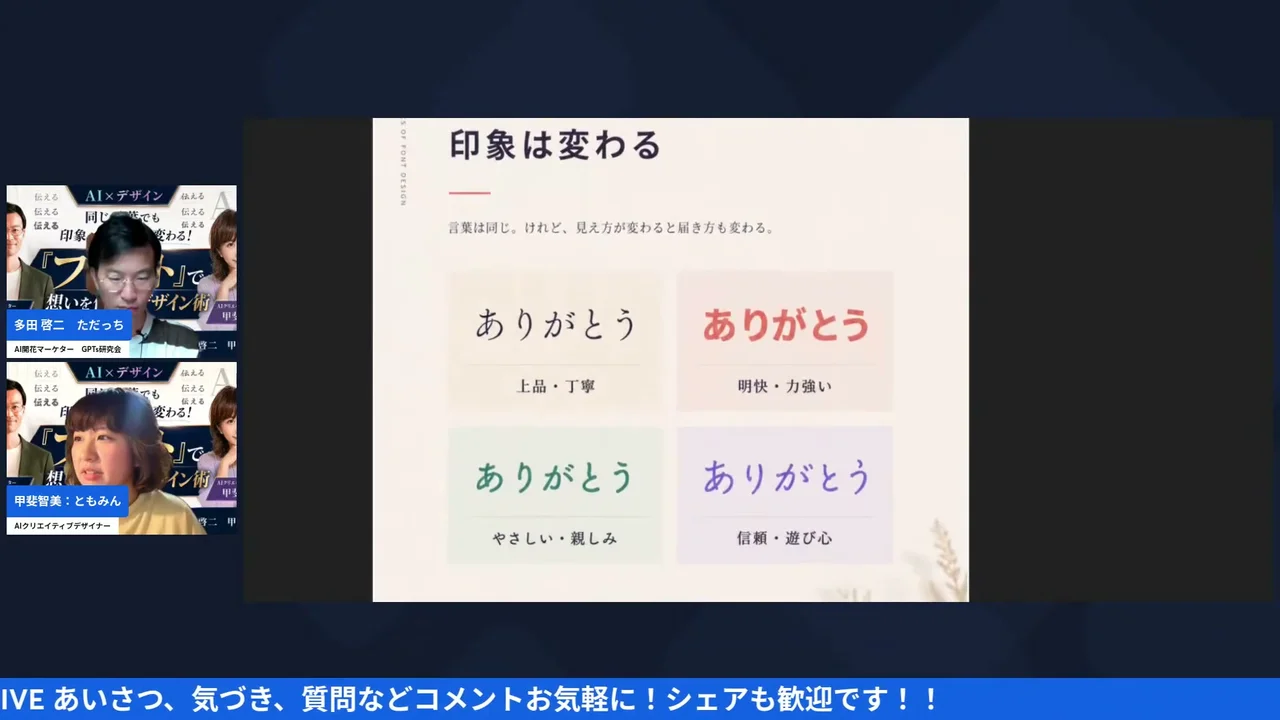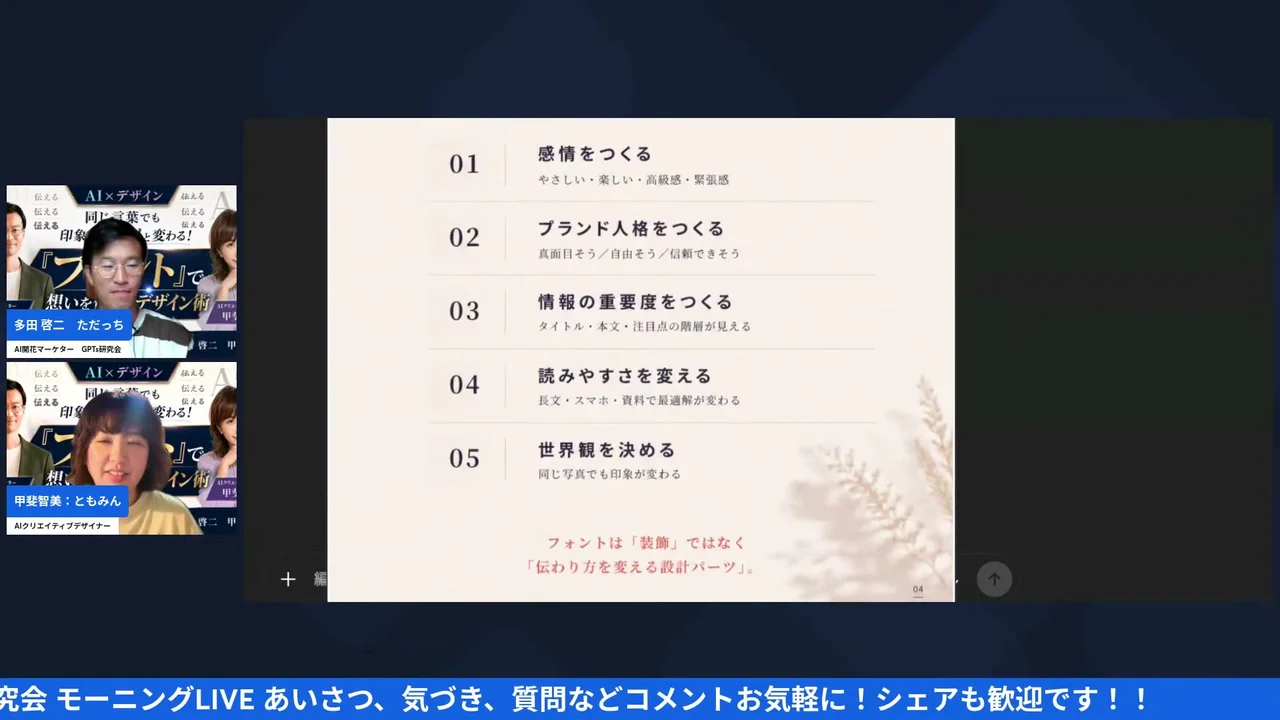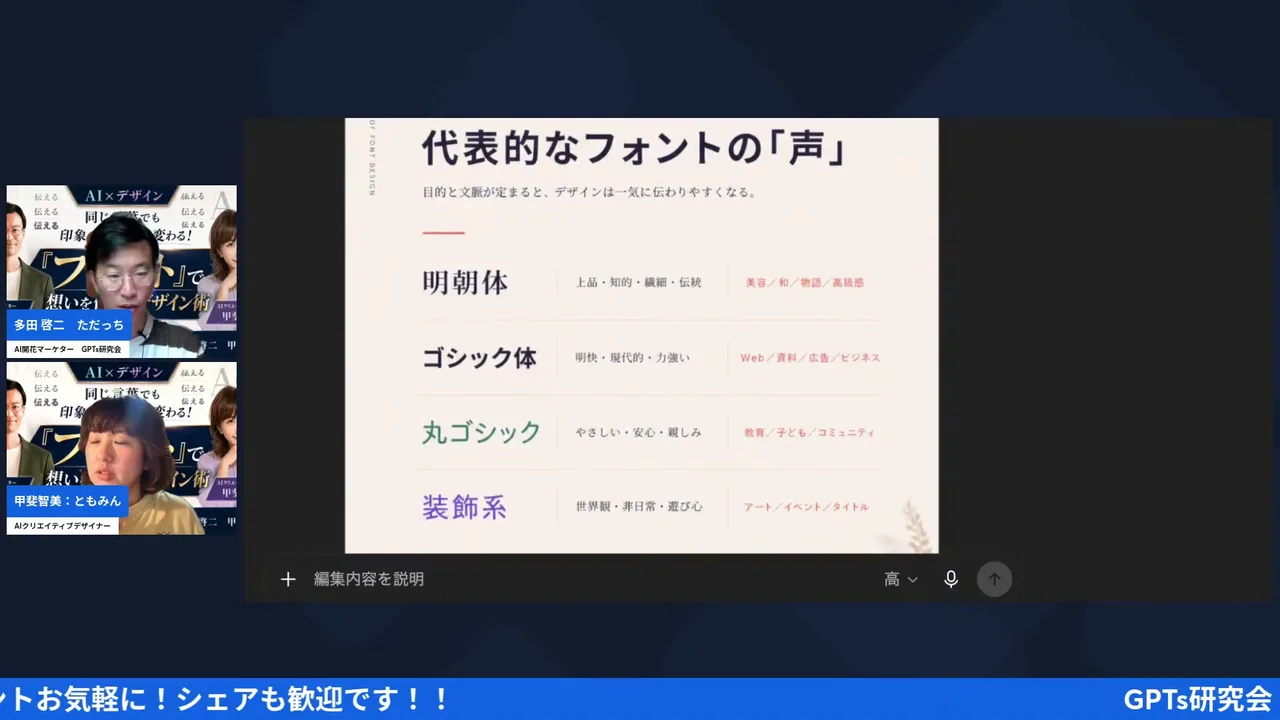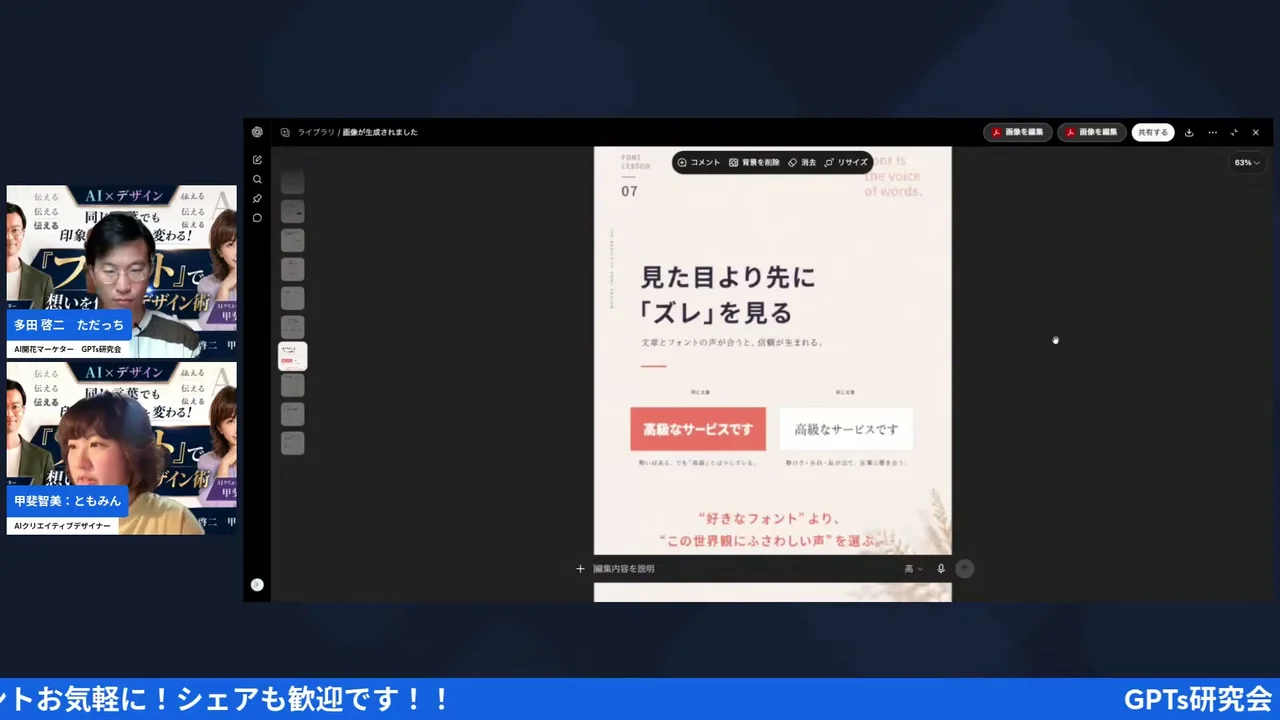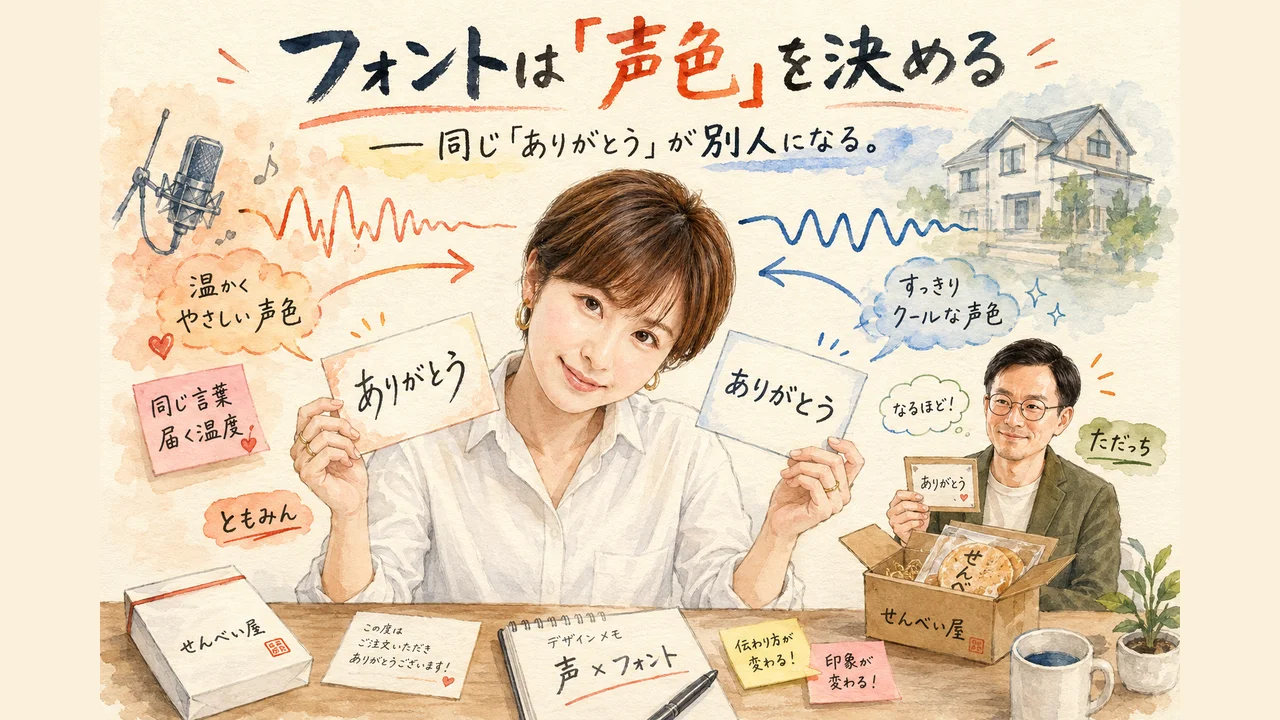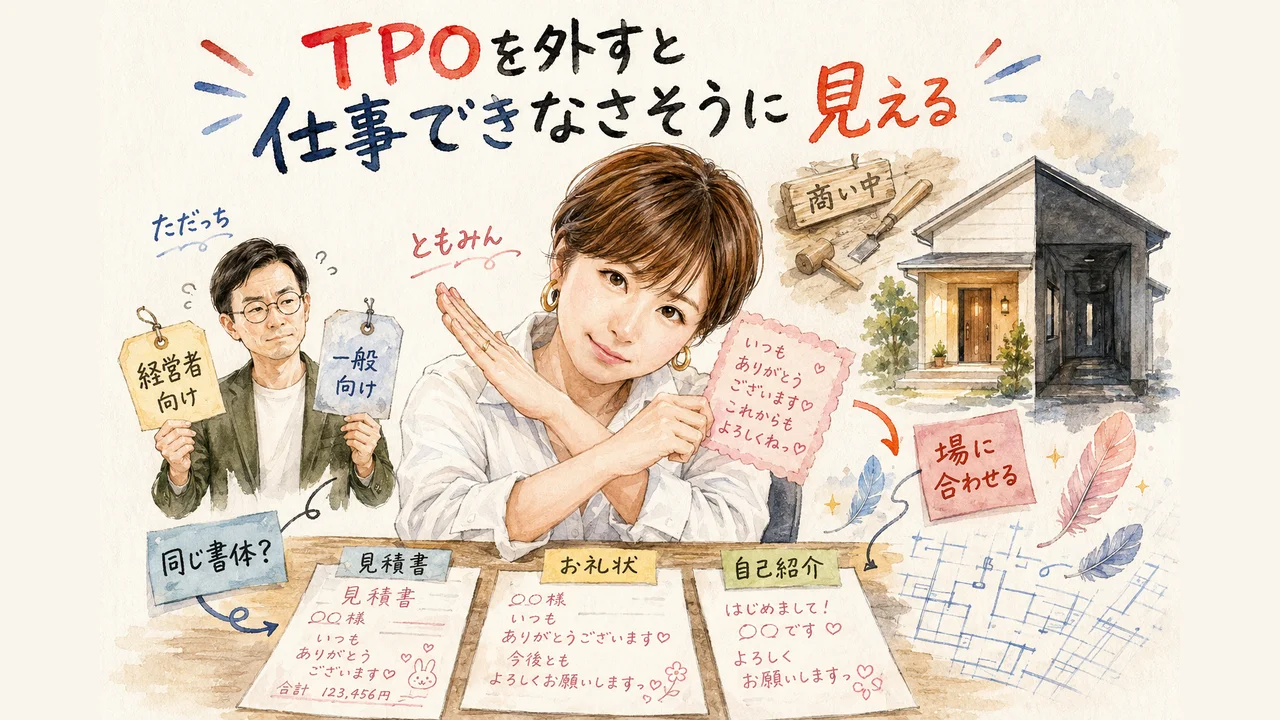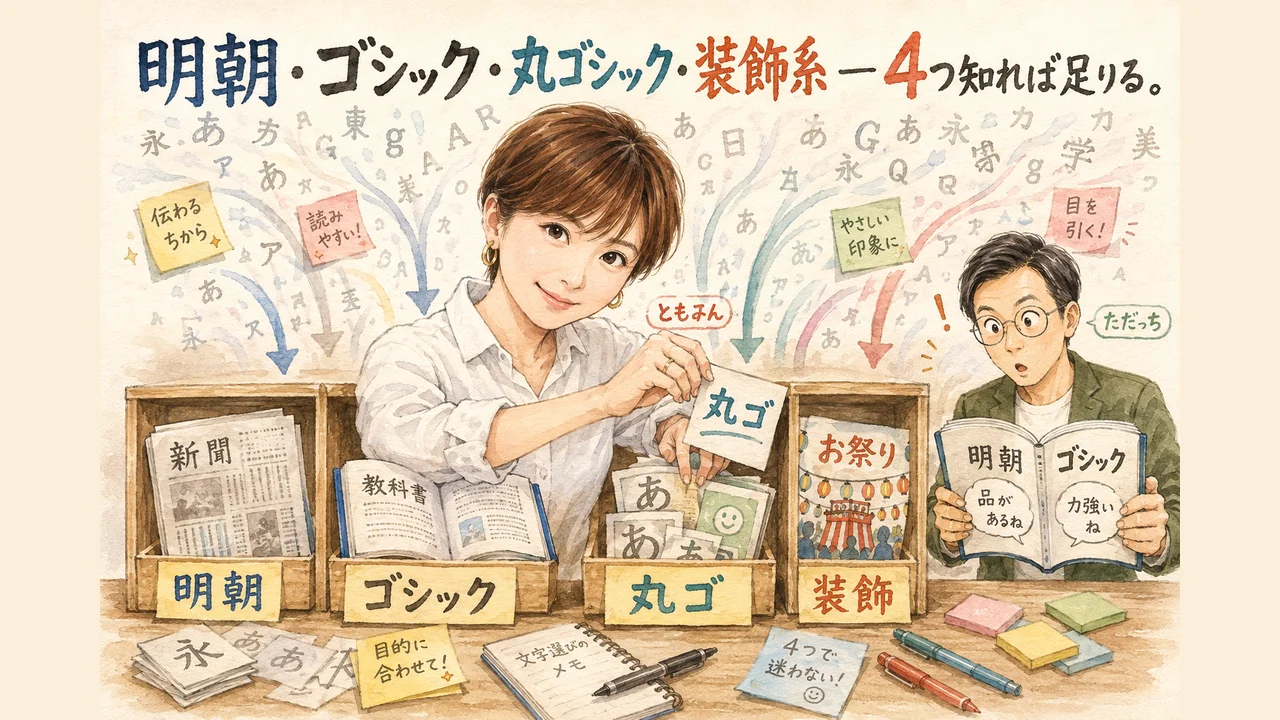
フォントの選び方で印象が激変する
明朝・ゴシック・丸ゴシックの使い分けとCanva実演|GPTs研究会 金曜あさLIVE
家事と子育てのスキマで経営する3方よしAI共創コンサルタントの田中啓之、ひろくんです。今回はただっち(多田啓二さん)とともみん(甲斐智美さん)の金曜あさLIVEを見て、私が受け取ったものを紹介するね。テーマは「AI×デザイン」。もっと絞ると、フォントの話です。
いやー、これがね。自分ずっと見落としてたなと思わされた。文字なんて、読めればそれでいいと思ってたんですよ。でね、ともみんが最初に置いた一言がこれ——フォントは声色を決める。文字は、読まれる前に、聞かれている。そういう話でした。同じ言葉でも、伝わり方はフォントひとつで変わる。
3行でわかるポイント
1. フォント=声色:文字情報は「何を言っているか」、フォントは「どう感じてほしいか」。同じ「ありがとう」でも別人になる
2. 使い分けは4種類でいい:明朝・ゴシック・丸ゴシック・装飾系。ベースは明朝とゴシック、あとはプラスアルファ
3. AIに指示する前段階:「なんか変」に自分で気づけるかどうか。文字と写真の一致感がないと、無意識で違和感が残る
フォント選びの全体像グラレコ|声色・TPO・4分類・3つの質問・Canva実演
フォントは「声色」を決める — 同じ「ありがとう」が別人になる
フォントは声色を決める|ともみん解説 同じ「ありがとう」をフォント違いで並べた比較画面
金曜の朝7時。画面の向こうで、ともみんがいきなり言い切ったんです。フォントは声色を決める、と。……いや、待って。文字に声も何もなくない? 私は正直そう思いました。ただっちも同じだったみたいで、すかさず「どういう意味でしょう?」って聞き返してる。で、そこからの説明が、ぐうの音も出ないくらい腑に落ちたんですよ。
▶ ともみん(7:28〜)
ともみん
「フォントは声色を決める。文字情報だったら何を言っているかということになるんだけど、どう感じてほしいか。だからね、ボーカルで言うと、声を選ぶことになるから。フォントにも普段用のフォントがあるんだよね。声を選ぶのと同じくらい大切だよっていうところですね」
ここ、2階建てになってるんだよね。1階が「何を言っているか」で、これは文字そのものが運ぶ。2階が「どう感じてほしいか」で、こっちを運んでいるのがフォント。同じ歌詞でも、歌う人の声が変わればまるで別の曲に聞こえる——あの現象が、紙の上でも画面の上でも起きている。そういう話でした。
例に出てきたのが「ありがとう」の4文字。細めの明朝で置いたときと、丸っこい手書き風で置いたときとで、届く温度がまるで違う。ともみんは、おせんべい屋さんからお客さんに送るダイレクトメールをたとえに出してました。同じ「ありがとう」でも、どっちのほうが相手に届く確率が高いか。考えたこともなかった。
▶ ともみん(9:31〜)
ともみん
「同じありがとうでも印象が変わるよって。同じだけど、見え方が変わると届き方が変わるから。ここだけでこれ、ちょっとフォントが全部違うものになってて、手書きのフォントだったり太さが違ったり色が変わったりっていうことになるんだけど、これだけで印象が変わるから。例えばお客さんにダイレクトメールとか、おせんべい買いましたって、お店の方から。このありがとうよりも、多分このありがとうが届く方が高いなみたいな感じ」
そこでともみんが持ち出したのが、Amazonで買い物したときに箱に入ってる小さなカード。ただっちも「カードみたいな」と即座に反応してました。あるある、って思わず声が出た。あの「ありがとう」って、けっこうな確率で手書きなんですよね。手書きだから、ほんの一瞬だけ目が止まる。ゴシックの活字だったら、ここまで気にならなかった気がします。
▶ ただっち(10:27〜)
ただっち
「そうだねー、確かに。手書きで考えると、本当に文字って個性が出たり人柄が出たりするから、そういう意味だと、このAI時代でも、このフォントっていうのって人から本当に伝わるよね。伝えてる思いがね」
ともみんはさらに、「ありがとう」にもTPOがあるって言ってました。カジュアルな「ありがとう」と、かしこまった「ありがとうございます」。言葉としては近いのに、フォントを変えるだけで、そのどっちに聞こえるかが変わってしまう。声を選ぶのと同じくらい大切だよ、と。
ただっちも「この視点はなかったですね」って素直に言ってました。私も同じです。デザインの話って、つい色とレイアウトに全部持っていかれるんだよね。文字は最後にちょこっと選ぶ、くらいの扱いだった。……そりゃ届かないわけだ、と思いました。
ここで私、けっこう反省したんです。チラシもLPも、色と写真と見出しの言葉で勝負するもんだと思ってた。文字そのものは「読めれば正解」の器だと。……でも受け取る側は、内容を理解する前に、もう声を聞いてしまっている。中身に届く前の一瞬で、この人はやさしそう、この会社はお堅そう、が決まってる。怖い。
💡 やさしく解説:文字情報とフォントの2階建て
同じ文章でも、読み手が受け取っているものは2つあります。ひとつは「何を言っているか」という中身。もうひとつが「どう感じてほしいか」という空気。前者を運ぶのが言葉で、後者を運ぶのがフォントなんだよね。だから、書いた文章がうまく届かないとき、原因は文章そのものじゃなく声色のほうにある場合がある、というのが今回のスタート地点でした。
TPOを外すと「この人、仕事できなさそう」に見える
フォントのTPO|伝達の設計というともみんの解説 TPO別フォント使い分けの解説画面
で、話は自然と「じゃあ誰に向けて書くのか」に移っていきました。ここでただっちが挟んだ整理が、経営者的にすごく実用的だったんです。読む相手が違えば、当然、選ぶ声も違う。
▶ ただっち(11:12〜)
ただっち
「そうだね。誰向けなのか、経営者向けなのか、一般の女性の方向けなのかによっても全然違うよね」
そこにともみんが被せてきた例が、この日いちばん背筋が伸びたところ。彼女の手書き文字は、本人いわく「漫画文字みたいな感じ」でかわいい。それ自体は素敵な個性なんだよね。ただ、その文字を企業向けの資料にそのまま使うとどうなるか。
▶ ともみん(11:20〜)
ともみん
「この企業様向けの資料に私が手書きで書いてしまうと、私の文字って漫画文字みたいな感じだからかわいらしい感じになるから、それで書いたらどうなるかっていうと、ぬくもりが伝わるよねっていうよりも、この人仕事できなさそうだよねってなるんだよね。文字って、そうじゃない? やっぱ。なんか人に思いを伝えればいいんだけど、資料として出すってなったら、ちょっとTPO的にはよろしくない」
うわー、と声が出ました。ぬくもりを届けたくて選んだ文字が、真逆の評価を連れてくる。悪意ゼロで、誠意もあって、それでも印象だけがズレていく。……これ、中小企業の現場でいちばん起きてるやつじゃないかな。ともみんは「人に思いを伝えるならいいんだけど、資料として出すとなると、ちょっとTPO的にはよろしくない」ってまとめてました。
逆もある。ものすごくお堅い企業の資料に手書きフォントは使わない、というのは誰でも直感でわかる。でも、その直感を言語化できてる人は少ないんだよね。ただっちが「フォントのお作法講座も希望します」って言ってたけど、まさにそれ。どういうときにどういう文字を使うか。心がけるだけで変わる、と。
そして、この日のいちばん本質っぽい一言が、ここで出てきます。フォントは飾りじゃない。
▶ ともみん(12:50〜)
ともみん
「伝達の設計です。装飾ではなく、伝わり方を変える設計のパーツ。そうなんだよね。だからこれ、ロゴとかみんなやっぱりこだわるじゃん。それと一緒だよね。名前を作ってるのと一緒だから」
装飾じゃなくて設計。ロゴと同じ扱い。ここを聞いて、私の中でフォントの置き場所が完全に変わりました。今までは「最後にちょっと整える工程」だったんです。デザインの終わりのほう、余力があったらやるところ。でも設計だとしたら、順番が逆になる。誰に何を感じてほしいかを決めた直後、写真より先に決まっててもおかしくないんだよね。
ここで、私にも思い当たる感覚がありました。相手も目的も違う書類なのに、フォントだけはずっと初期設定のまま使い回してしまう——そういうこと、意外とあるよなと。中身は書き分けていても、声だけ全部いっしょだったら、伝わり方はやっぱり変わってしまうんだろうな、と思いました。
もうひとつ、ともみんの言葉で見落としちゃいけないのが「名前を作ってるのと一緒」というところ。ロゴと同じ重みで、フォントも扱われるべきものなんだな、と受け取りました。
▶ 11:12〜 LIVE映像で確認 「この人、仕事できなさそう」に化ける瞬間を聴く テキストでは伝わらない判断のテンポと間がここにある
03
明朝・ゴシック・丸ゴシック・装飾系 — 4つ知れば足りる
明朝・ゴシック・丸ゴシック・装飾系の4分類 明朝・ゴシック・丸ゴシック・装飾系を並べた比較スライド
ここからが実務パート。フォントって世の中に何千種類もあって、それが選べない理由になってるんだよね。ともみんの整理は、ざっくり4つ。明朝体、ゴシック体、丸ゴシック、そして装飾系。装飾系というのは、ちょっと崩したようなやつ。アートとかイベントとかポスターで使うタイプ。
画面に4種類を並べてもらうと、ただっちの第一声は「ゴシック体が見慣れているせいか、パッと入ってきやすい」。私も同じ感想でした。ところが、ここに落とし穴があるんです。
▶ ともみん(14:30〜)
ともみん
「そう、ゴシックが実際に目には入ってきやすいけど、教科書とかって明朝体だったりするんだよね。だからこのウェブで目立つ文字と、書面での文字って違うんだよ。新聞の文字とかは明朝の方が多くない? だから印刷してる文字とかで変わるじゃない。ちょっとオフィシャルの、公的な文書とかだったら絶対明朝なんだよ」
言われてみれば、新聞も明朝。役所から届く公的な書類も、まず明朝。あれ、丸文字で書かれてたら一発で信用がなくなるよね。ともみんも「オフィシャルな公的文書だったら絶対に明朝なんだよ」って言い切ってました。画面で目立つ文字と、紙で読ませる文字は、そもそも仕事が違う。ここを混同したまま作ってる資料、私の過去にも山ほどあります。
で、丸ゴシック。これは対象がガラッと変わる。